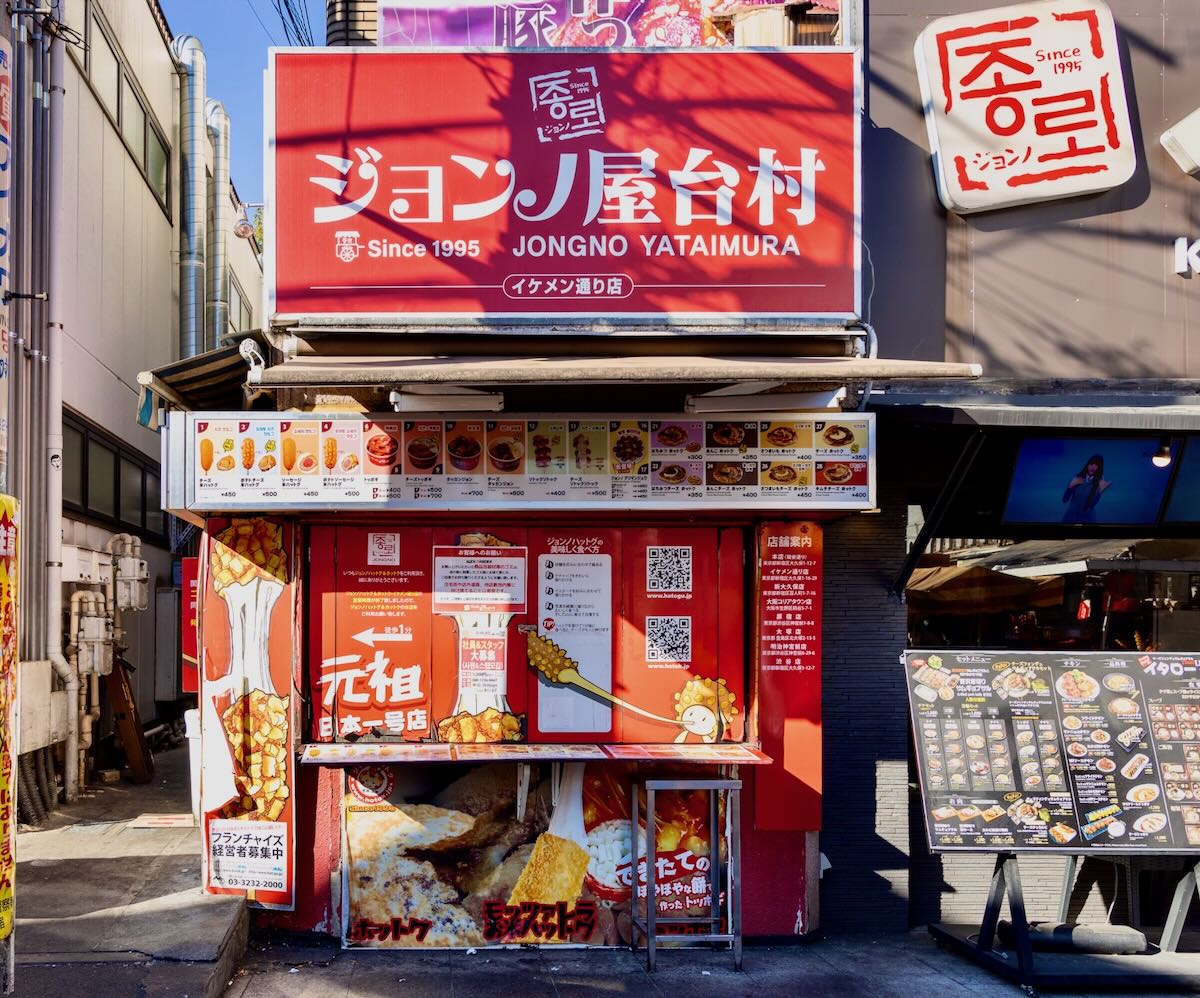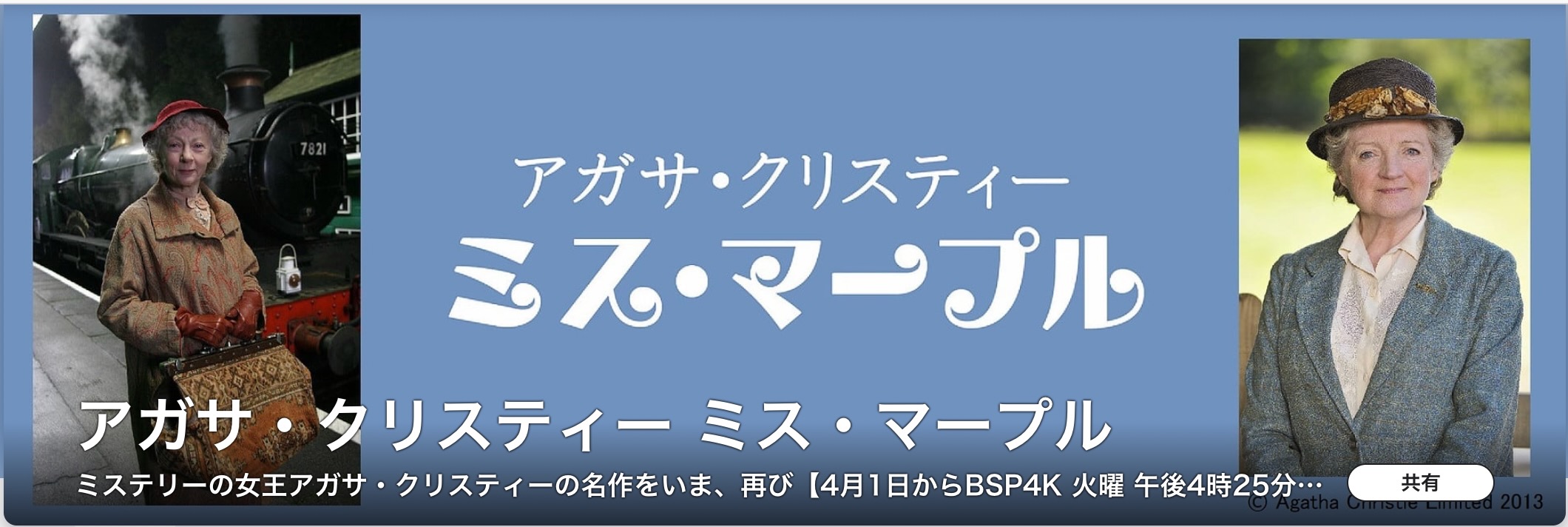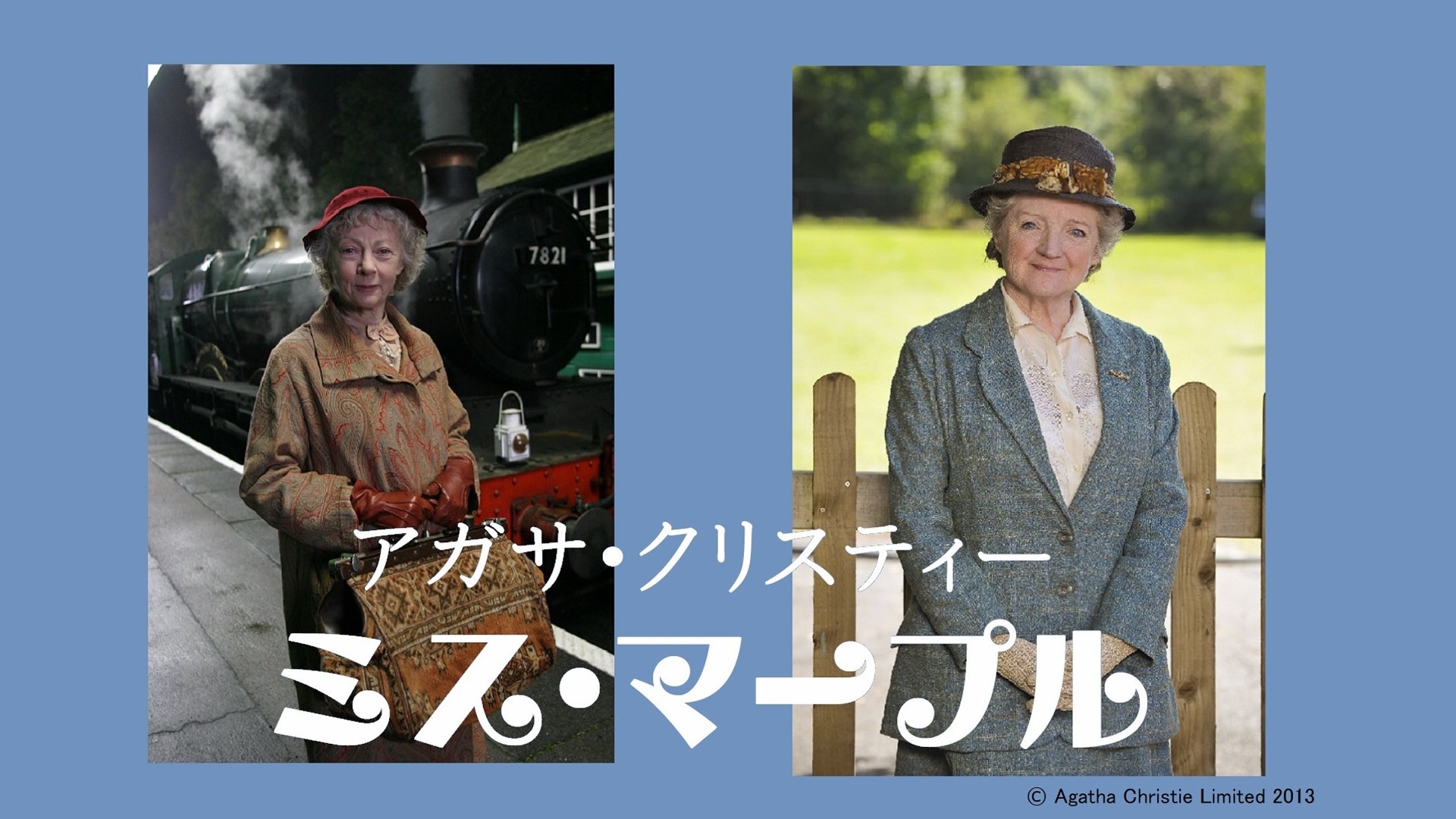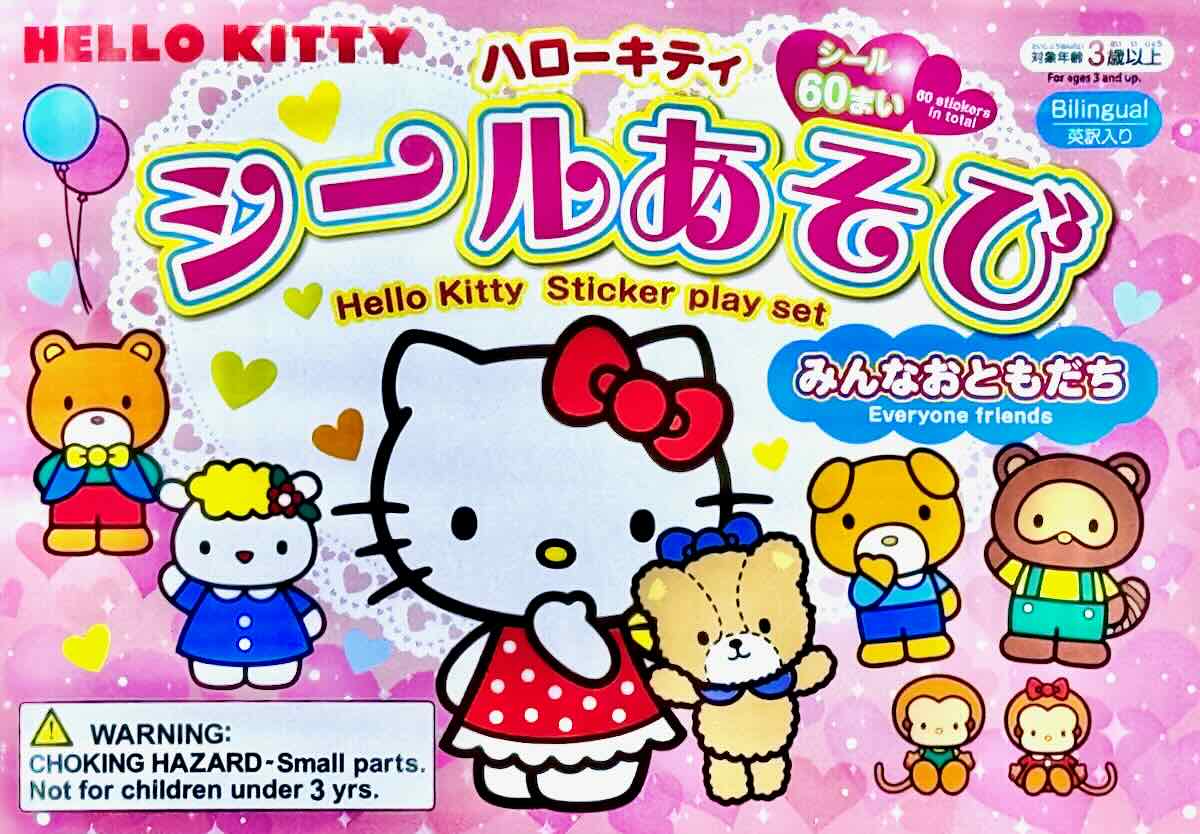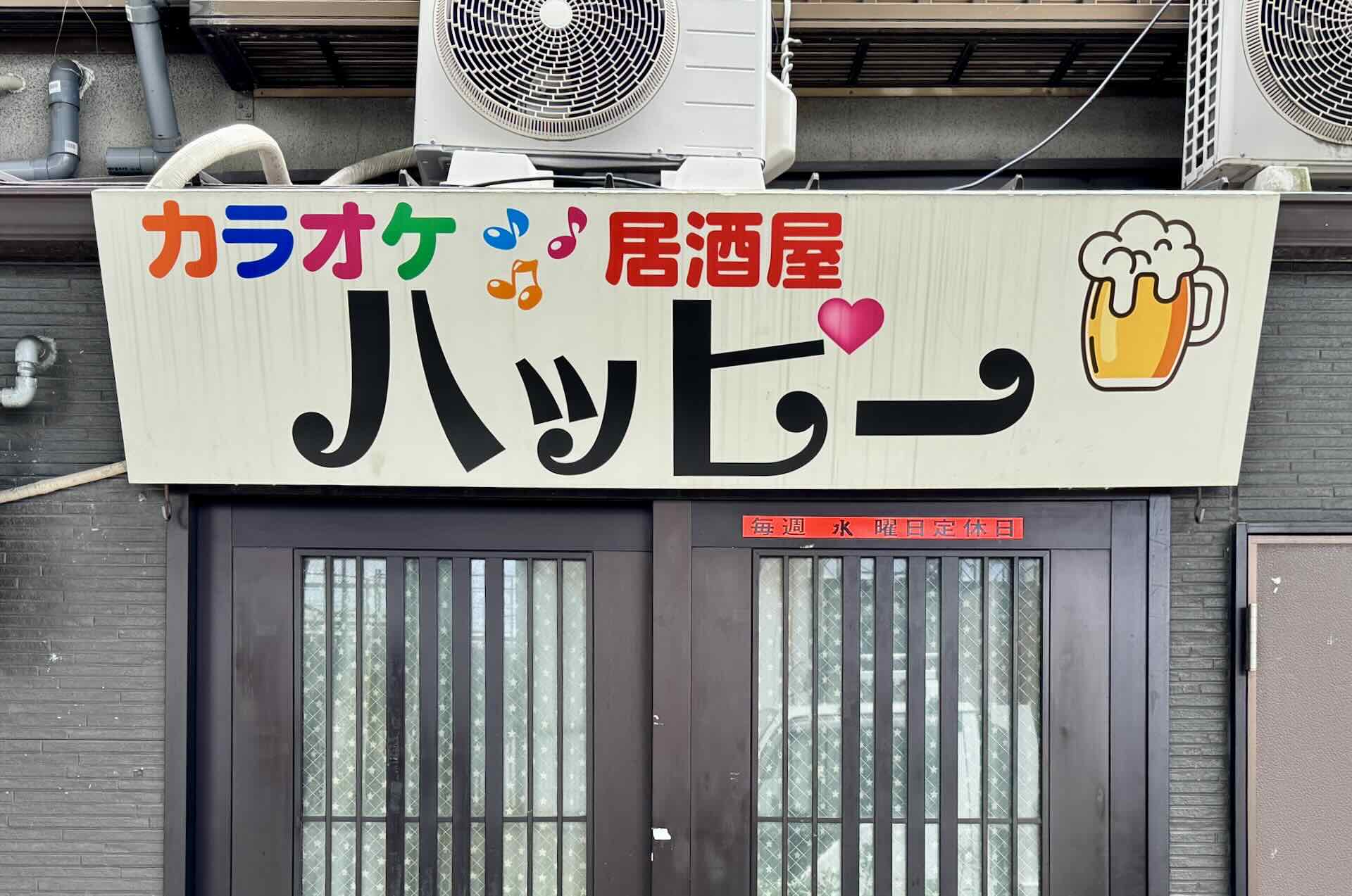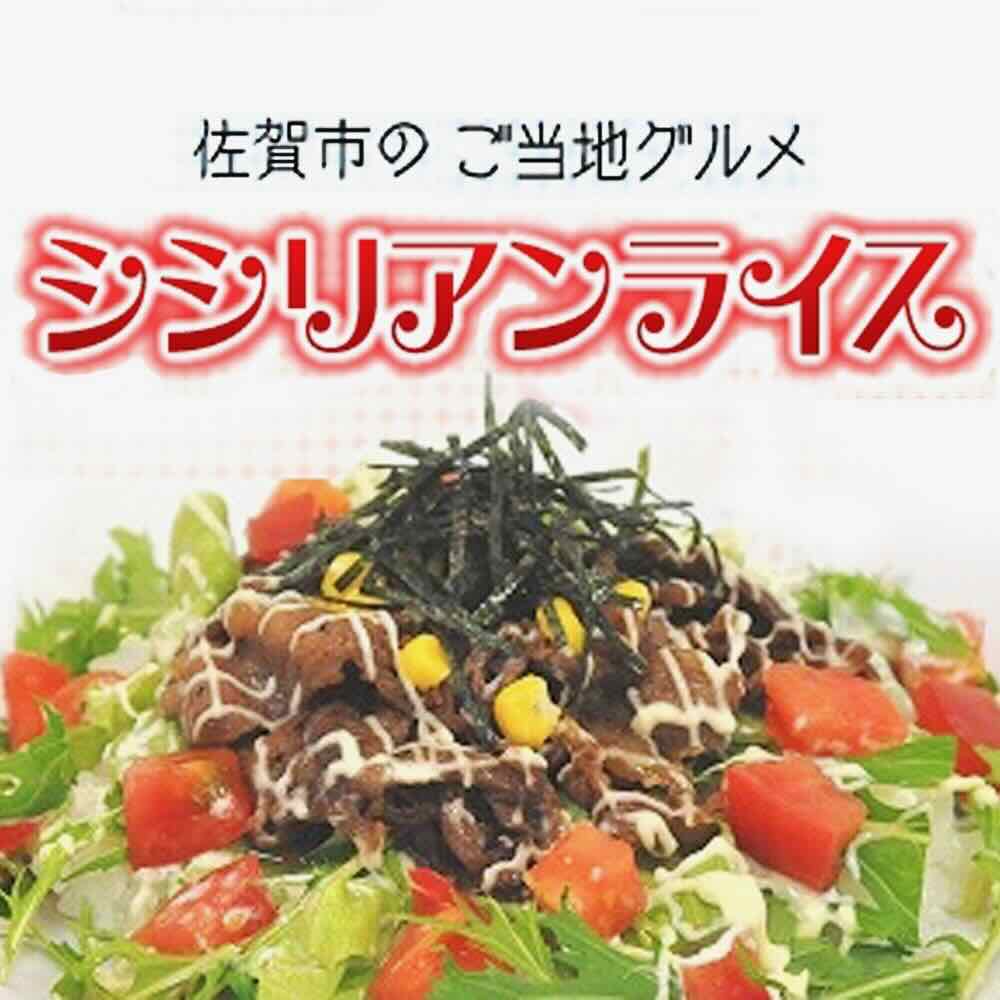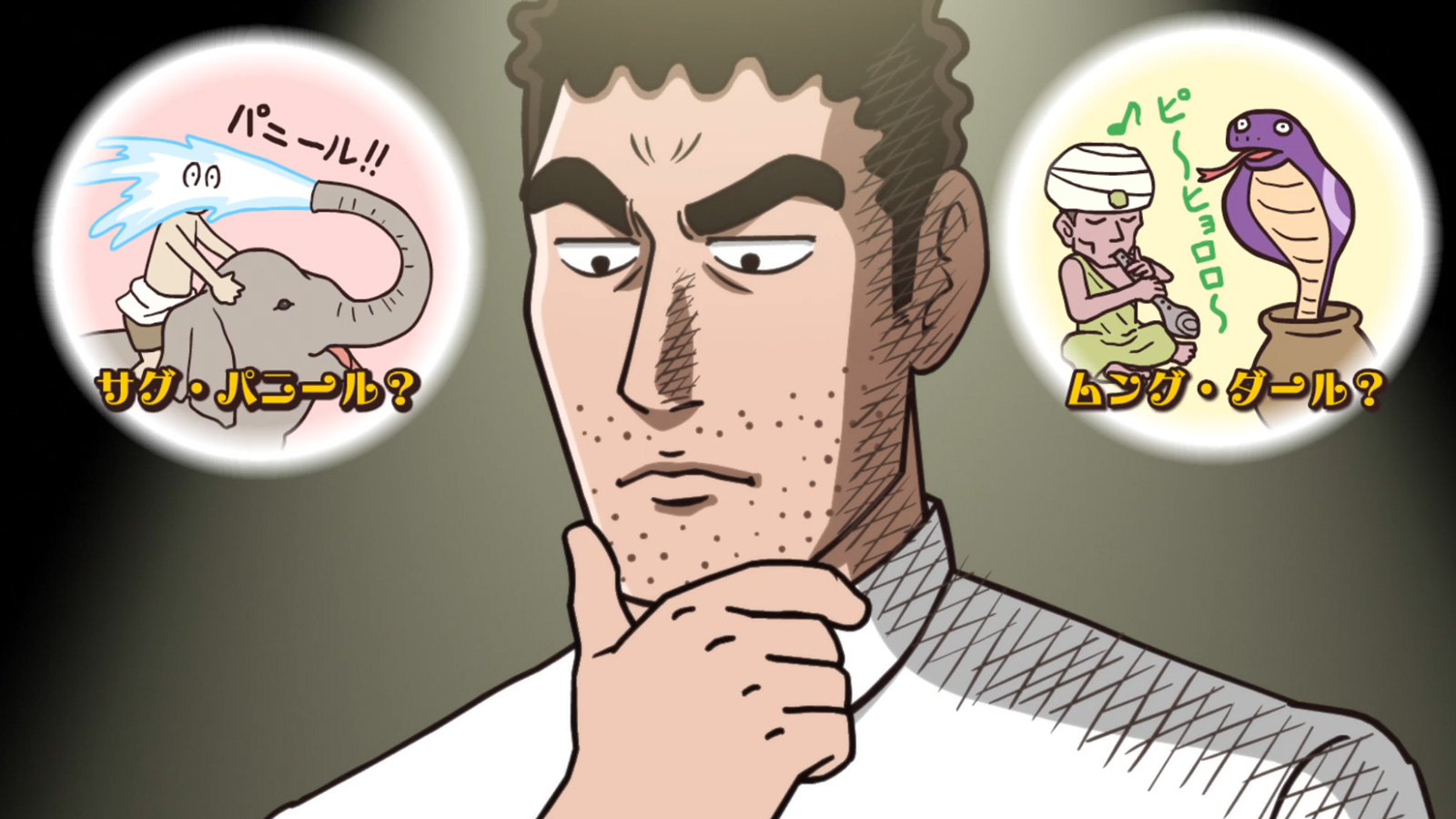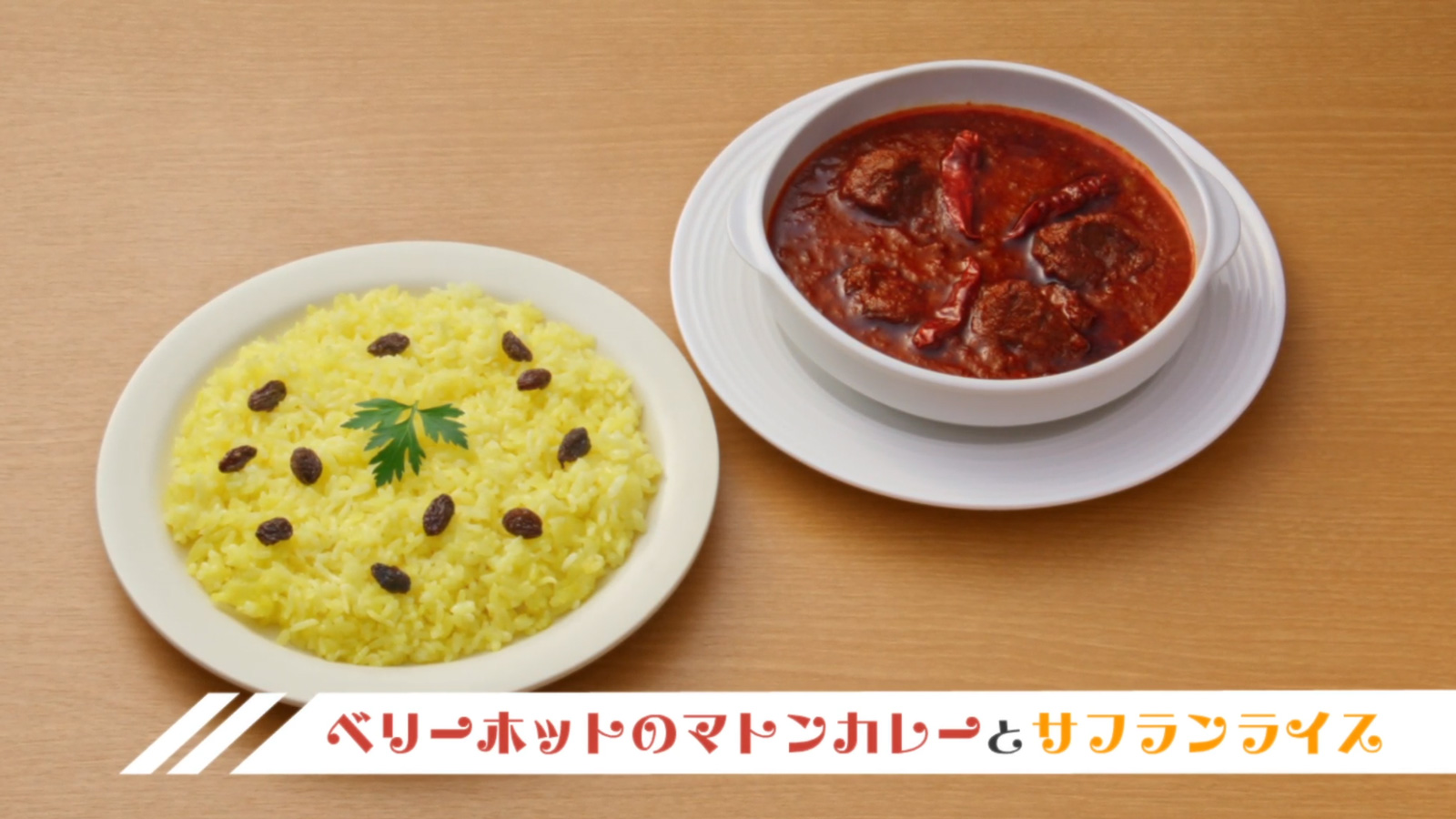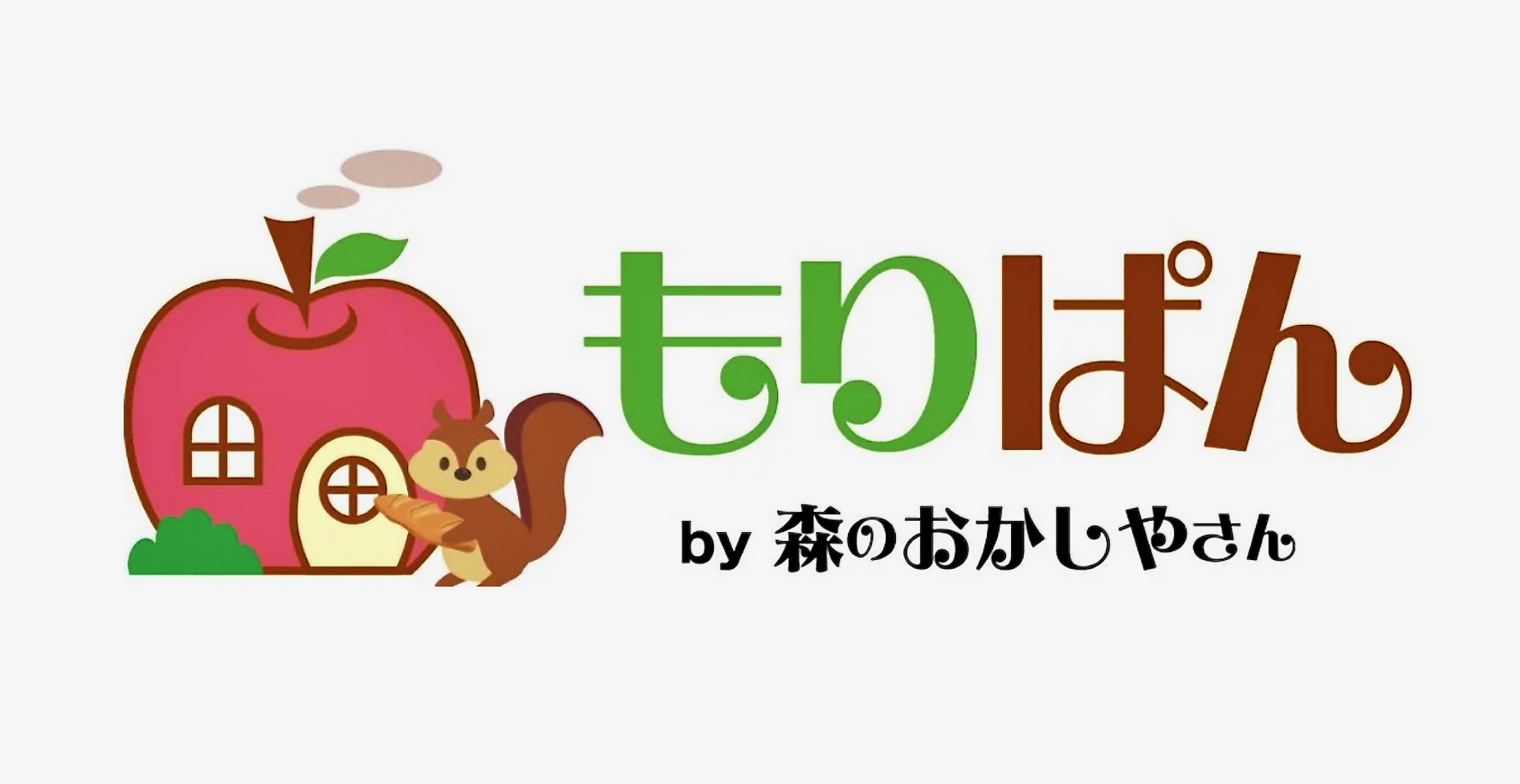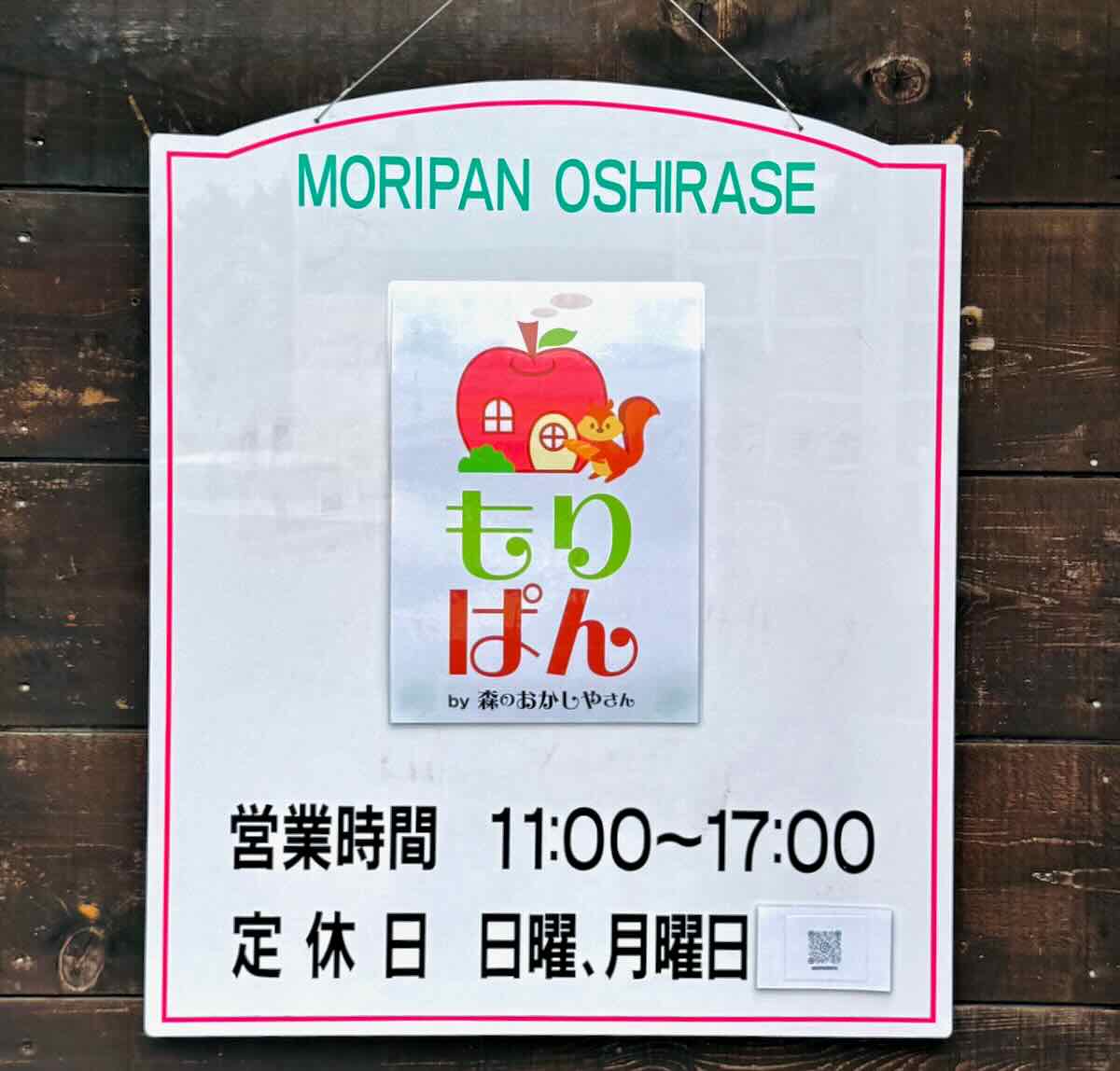
タイプラボが頒布している「えれがんと平成明朝」だけでなく
かな書体「えれがんと」は、フォントワークスからも販売されています
ハロウィン さとうゆたか
10月31日は、ハロウィンだそうだ。
ネット上で「えれがんと書体」が使われているハロウィン画像を探した…。
これも。
江東区の交差点で見かけた、古い初期バージョンの「えれがんと」書体。
これは、ネットで拾ったもの。
旅行社広告 大阪のうめ吉
読売旅行関西予約センターの「読売新聞」折込みの全紙大4ページものです。
旅行広告、大きいので関連部分です。
「ハウステンボス」の部分。「ハ」「ス」が化工されていますが。
両端の文字が、左右対称になるよう上手に加工してありますね。
懐かしいです。 吾亦紅
ありがとうございます。懐かしいです。私が制作したものです。
施設のロゴ さとうゆたか
山形県新庄駅に直結の鉄道展示施設名。
店名ロゴ さとうゆたか
神戸三宮の洋食店。
あ さとうゆたか
最近は、酒場の文字を外したようです。
居酒屋の看板 みきお
地元の居酒屋の看板で、えれがんとフォントを見かけました。
濁点がオリジナルとは異なり、棒線を2本書き加えたように見えるので、無料お試し版(清音のみ)ですね。
濁点の処理を見ると、たしかに無料版フォントでしょうね。
商品版なら、もっとキレイなものが簡単に作れるのに、残念です…。
山形のフルーツ さとうゆたか
「フ」と「ル」の字間が狭すぎるのが、ちょっと残念…。
これはタテ型。
佐賀市の名物 さとうゆたか
シシリアンライスのロゴ。
これも。
漫画の表紙タイトル さとうゆたか
いま販売中のビッグコミック増刊号。
「オシメンガムスメ」という漫画。
作者は、石原まこちん。
各文字に、すこしずつ手が加えられている。
「シ」の二画目が下げられているのは、イヤだな…。
ずいぶんと、時が過ぎたが、ネット漫画のサムネール画像。
ゲーム関連のラジオ(?)番組 takumi
スクエニのゲーム「オクトパストラベラー」の番組。
ロゴ(オクトラジオ)に「えれがんと」が使われています。
わざわざ加工して使ってる割には字間調整が雑な気もしますが…。
カドが微妙に丸くなっているので、FWに提供した「えれがんとUB」のようです。